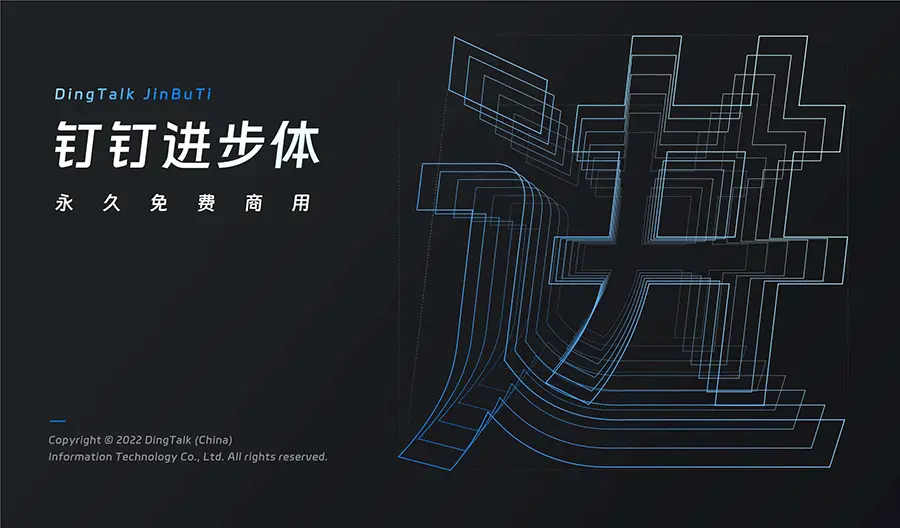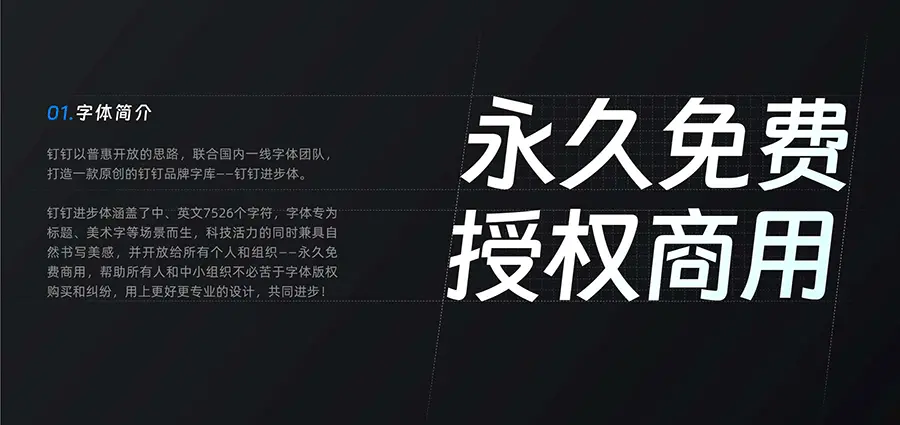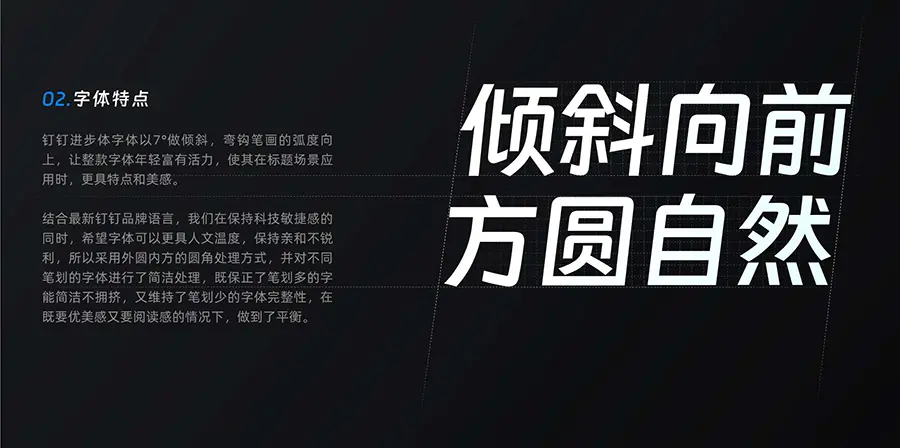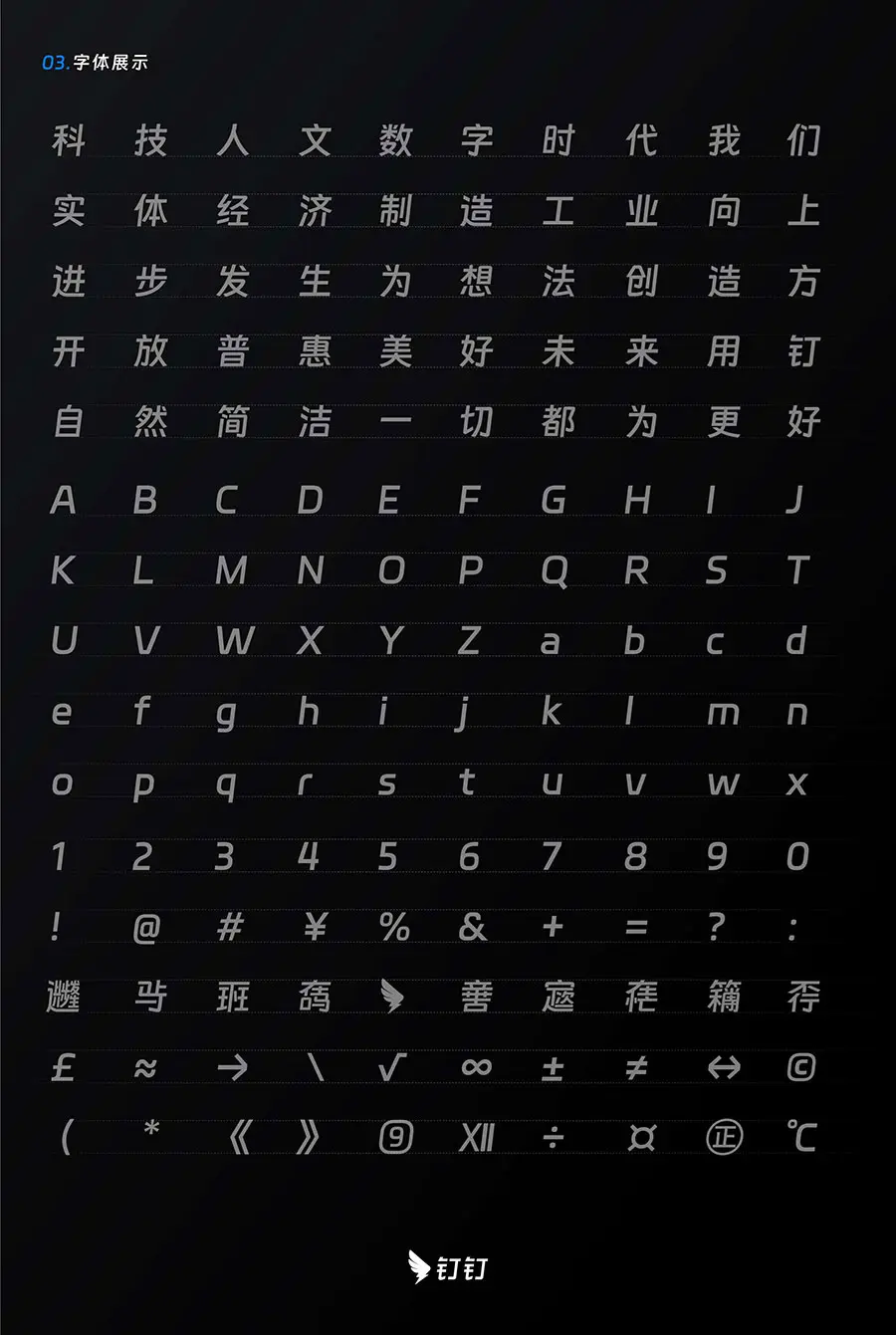
2022年12 月 28 日上午,釘釘在杭州正式開啟 7.0 版本產品發佈會。發佈會上,釘釘總裁葉軍詳細解讀了釘釘 7.0 版本的新功能,同時推出了漢儀字庫為其量身打造的定製字體“釘釘進步體”。
釘釘以普惠開放的思路,聯合國內一線字體團隊,打造一款原創的釘釘品牌字庫——釘釘進步體。 釘釘進步體涵蓋了中、英文7526個字符,字體專為標題、美術字等場景而生,科技活力的同時兼具自然書寫美感,並開放給所有個人和組織——永久免費商用,幫助所有人和中小組織不必苦於字體版權購買和糾紛,用上更好更專業的設計,共同進步!